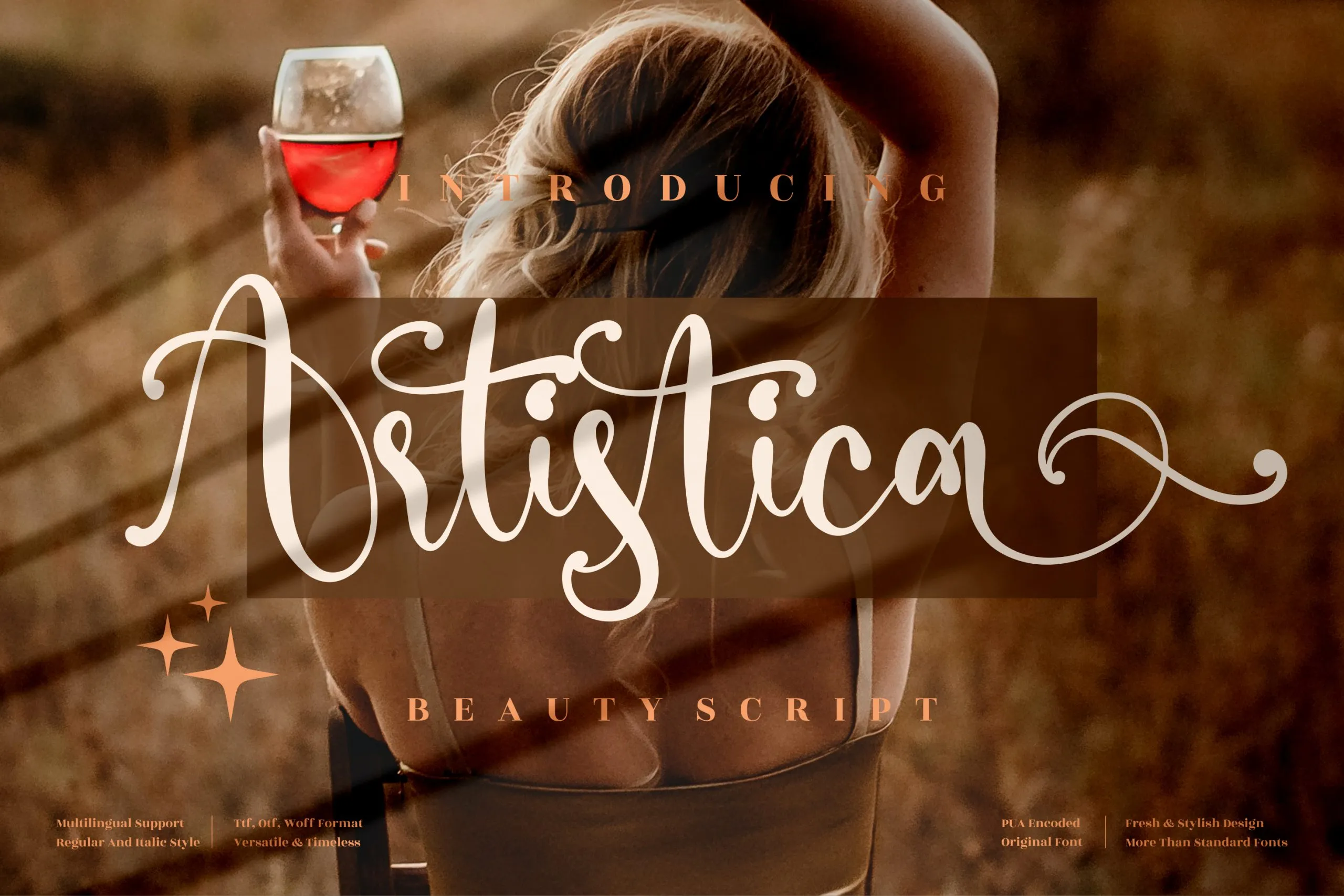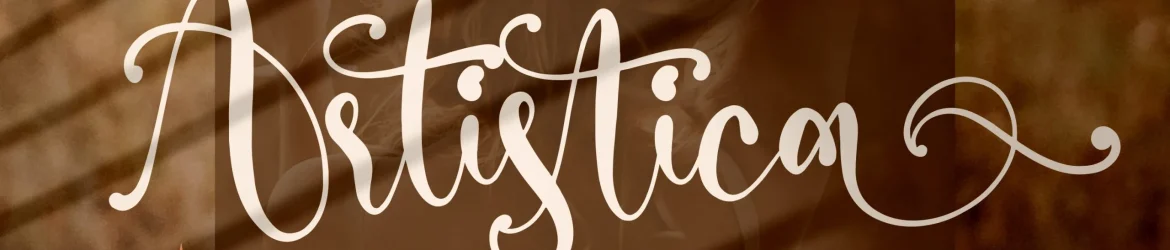
Artistica Script Font – Download Grátis
A ‘Artistica Script Font’ é uma elegante tipografia cálida criada pelo estúdio Perspectype Studio. Ela traz um toque romântico e sofisticado, perfeitamente adaptável para projetos variados como logotipos, embalagens de produtos, cartões de nome, selos e até mesmo para capas de livros. Suas linhas fluidas e detalhes finos tornam-a uma escolha ótima para estilos criativos em design gráfico, seja para um projeto de homenagem, postere ou embalagem personalizada. Além disso, a fonte tem uma versatilidade que permite sua utilização em diversas áreas da criação visual, como adesivos de prato ou camisetas personalizadas. A ‘Artistica Script Font’ oferece um toque encantador e singular para seus projetos.